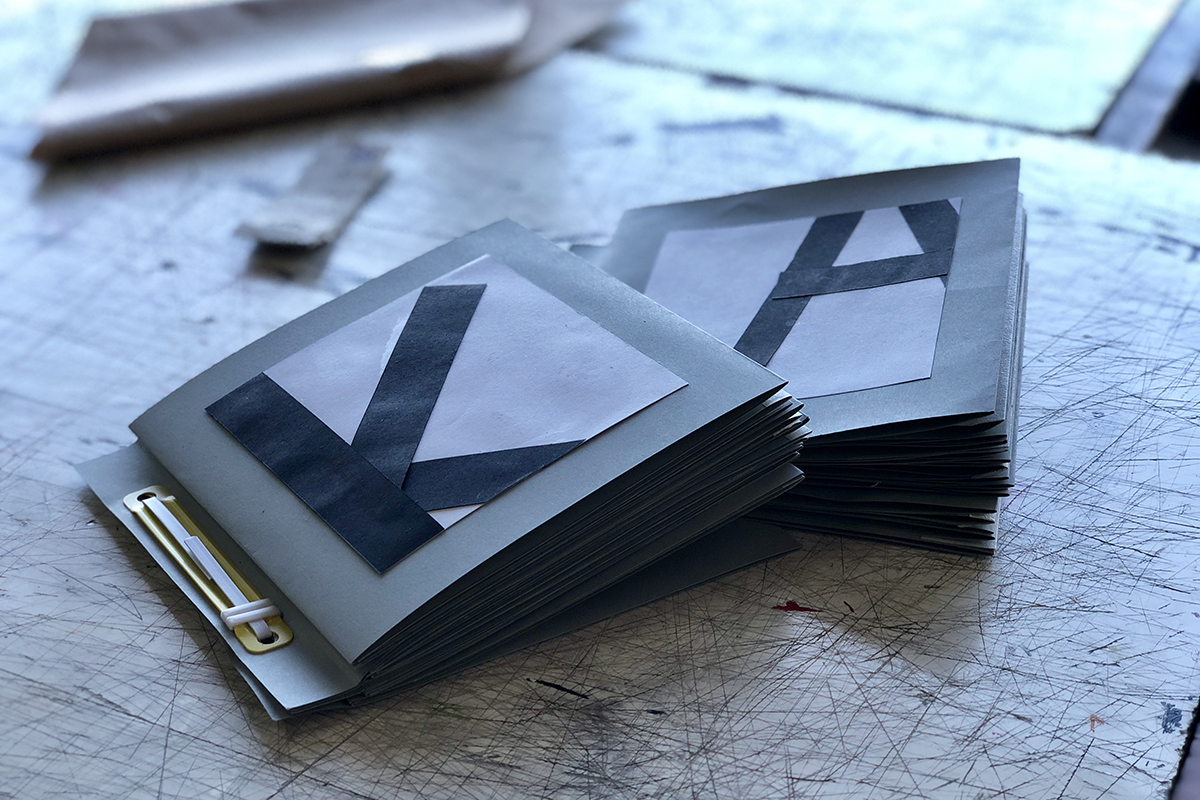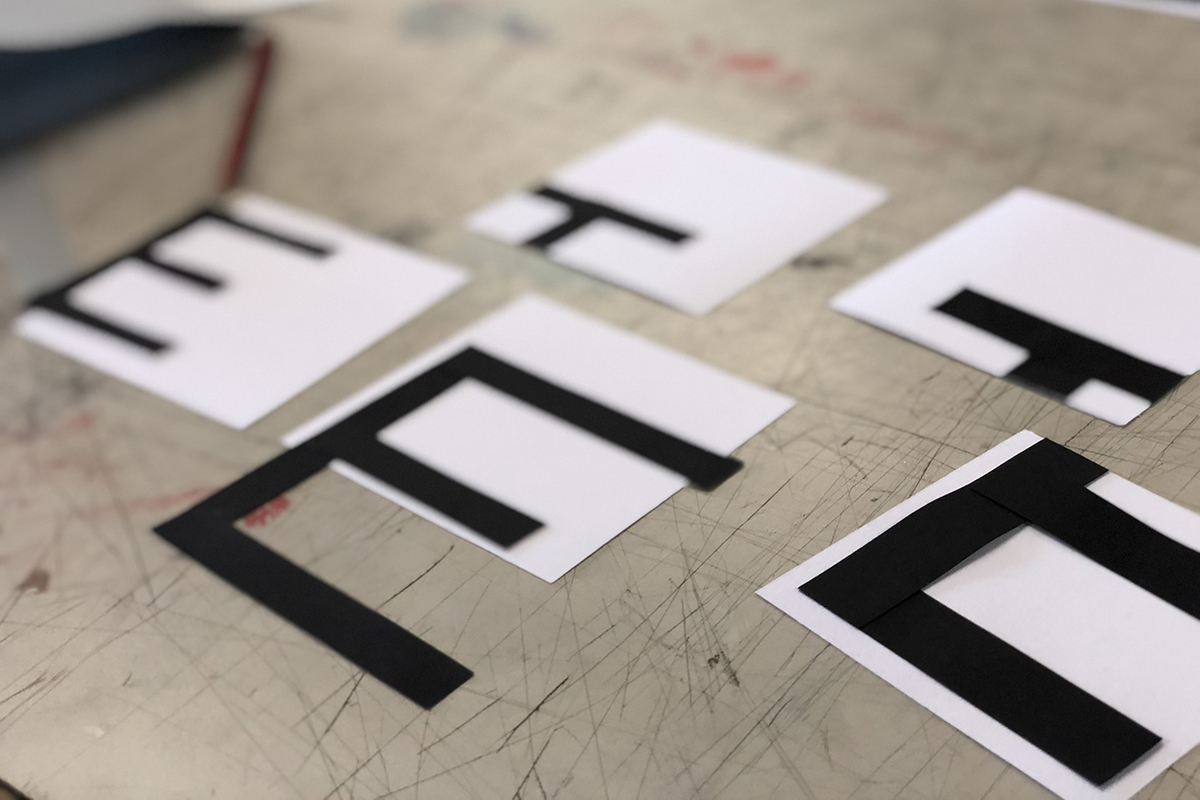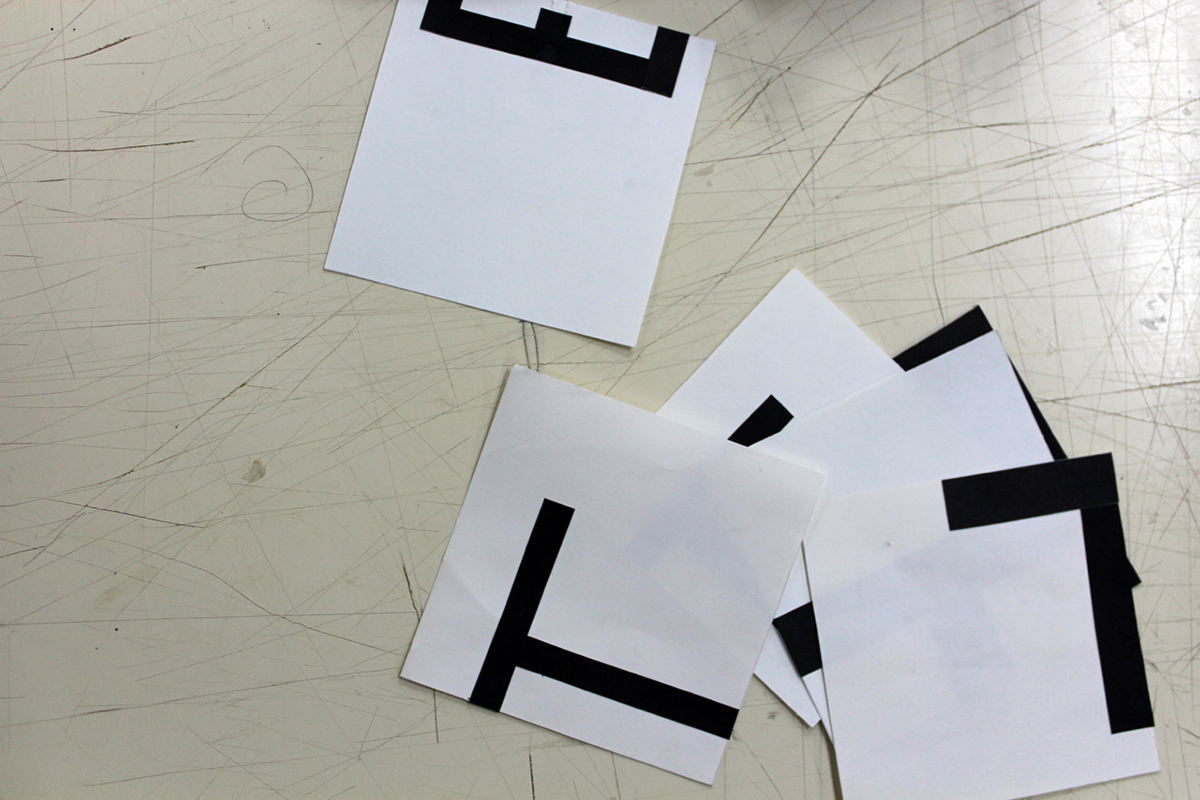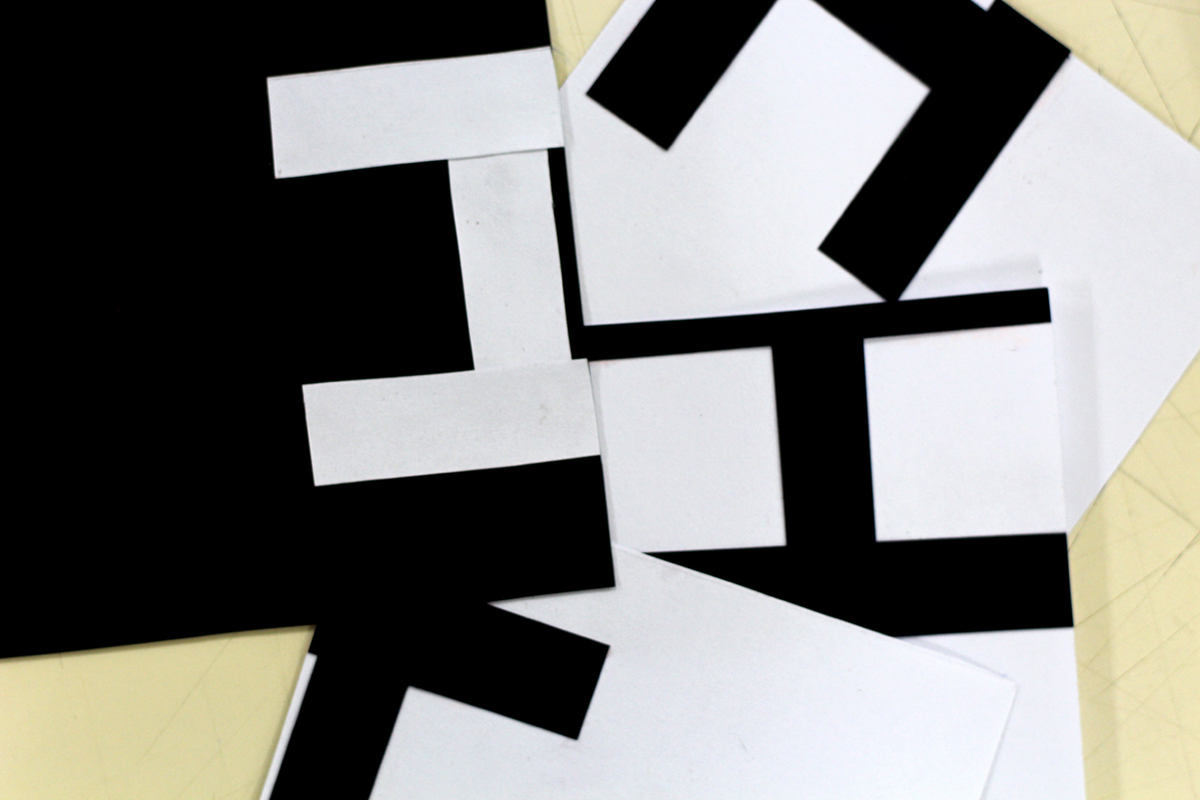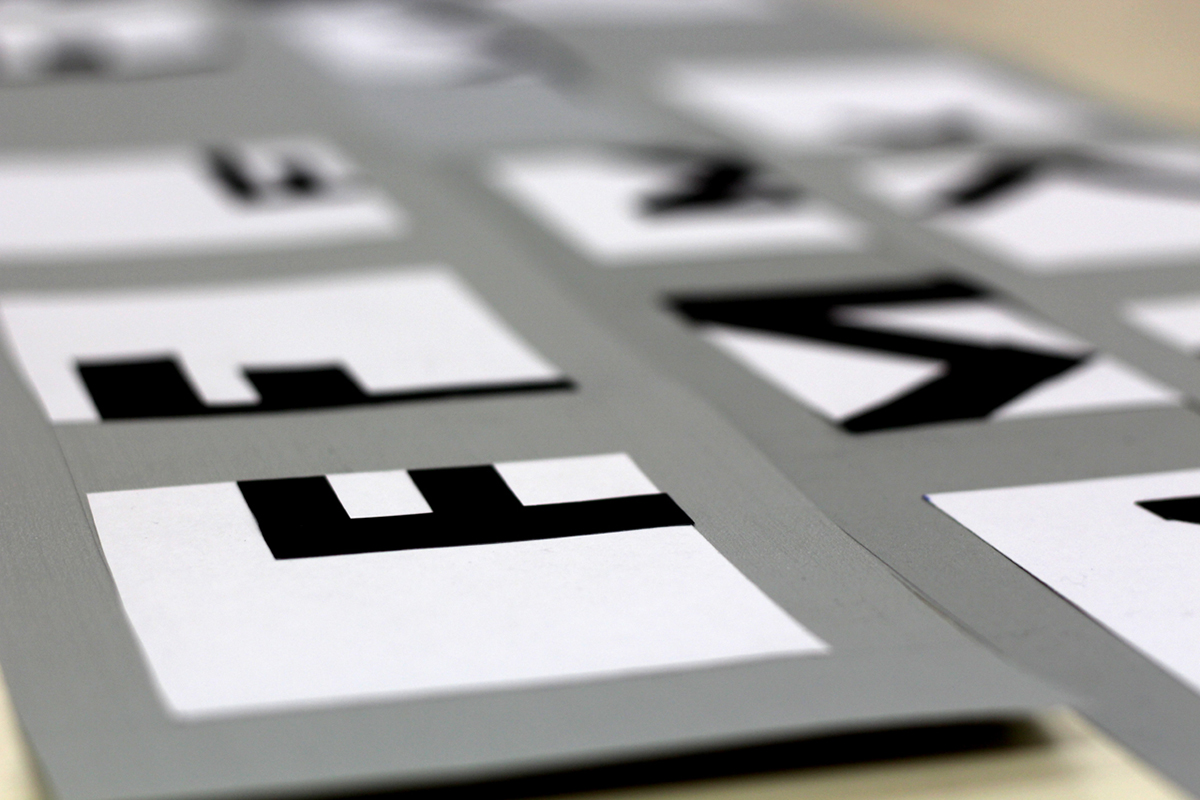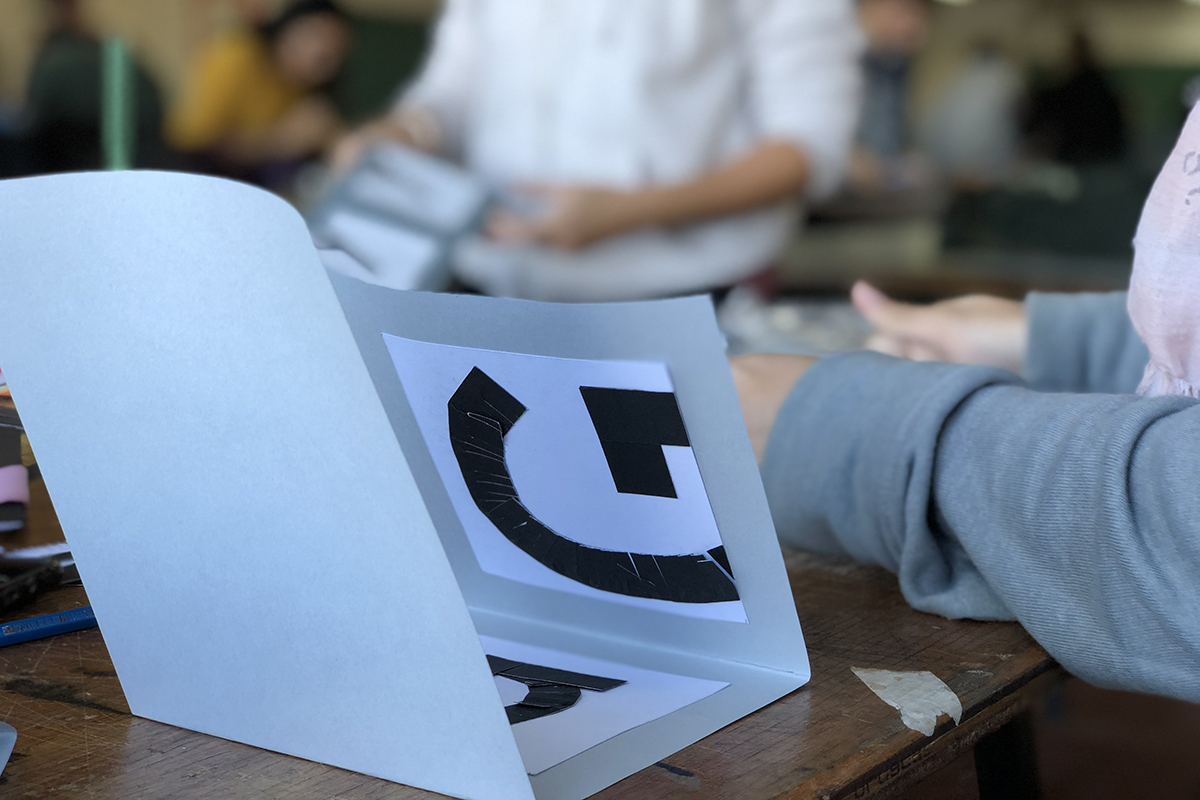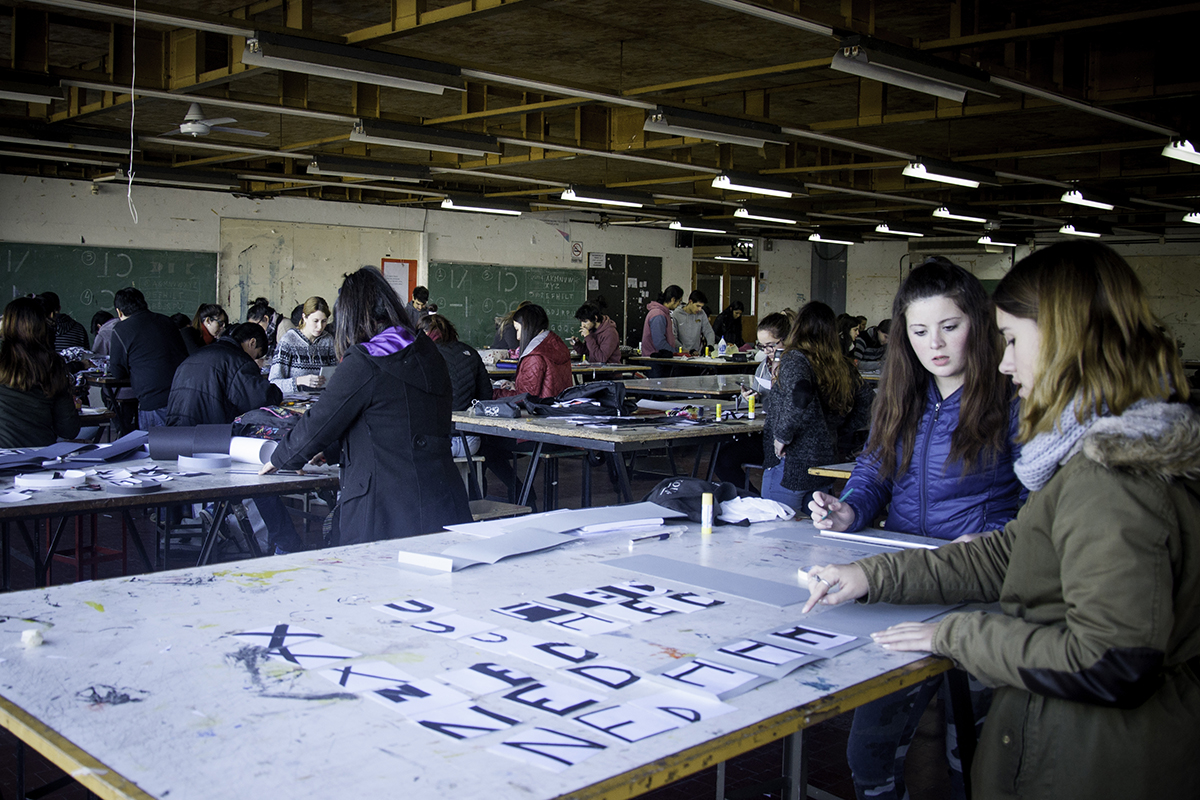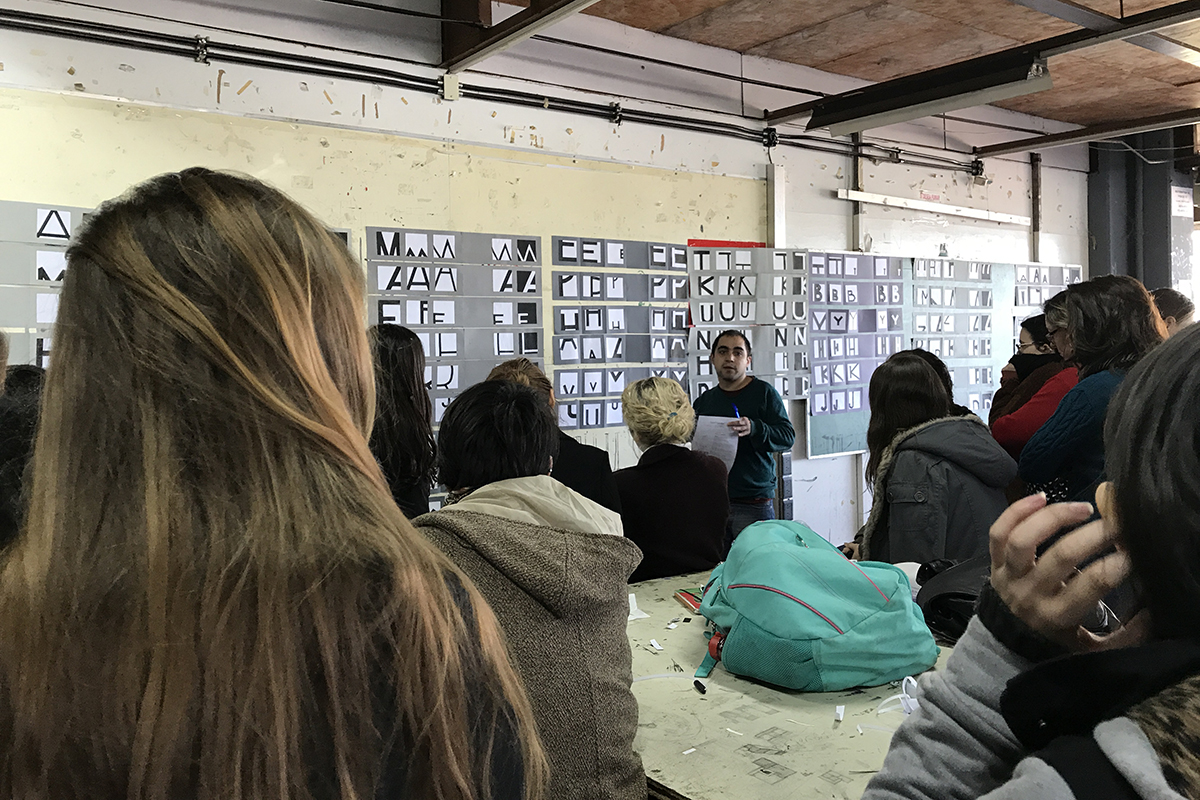
Forma y contraforma
Reconocimiento del signo
Este trabajo completa la serie de los tres primeros ejercicios del taller. 1a: observo el entorno, 1b: descubro mi trazo, 1c: me introduzco en la tipografía para comprender los rasgos que identifican a las letras mayúsculas al llevar, el signo tipográfico de estructura simple, al límite de su reconocimiento.
Este ejercicio que nos permite abordar las relaciones figura-fondo, la variación del trazo, la relación positivo-negativo, el espacio gráfico, la organización y el trabajo en equipo.
Es un esquicio de una jornada.